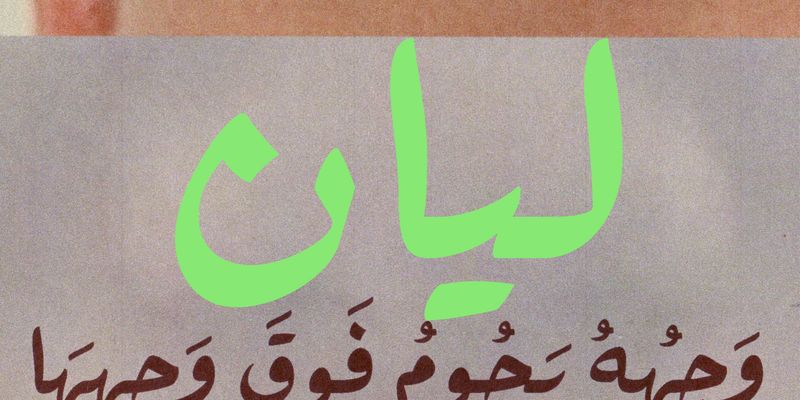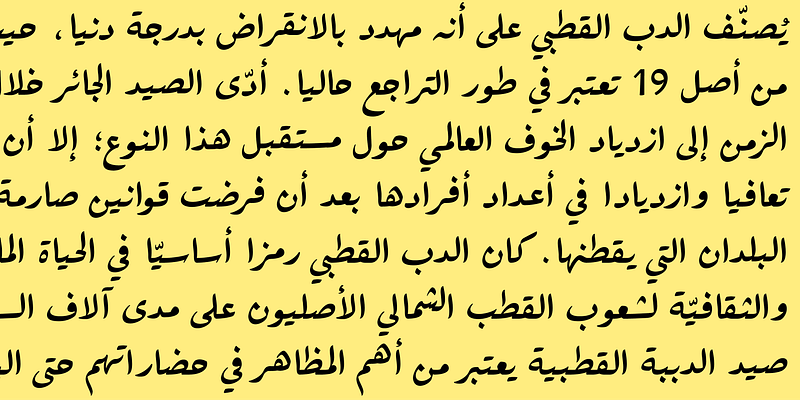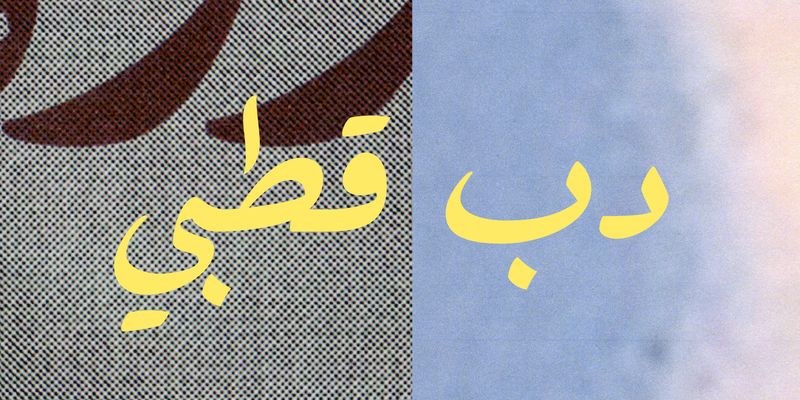
Layaan ist eine frische Interpretation des Ruq’ah-Stils, konzipiert für den redaktionellen Gebrauch. Es ist eine zeitgemäße Interpretation des traditionellen Schreibstils, der sein starres Grundgerüst beibehält, aber ein weicheres, zugänglicheres Gefühl vermittelt. Jawaher Alali entwarf die Schrift, die Elemente der Kalligrafie und der Handschrift miteinander verbindet, um einen Raum zwischen formell und lässig zu schaffen.